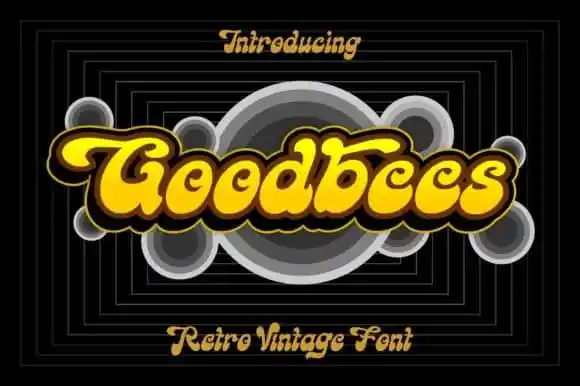
Goodbees Display Font – Download Grátis
A Goodbees Display Font é uma escolha perfeita para quem busca dar um toque vintage a seus projetos digitais. Inspirada no estilo retro dos anos 70, essa fonte se adequa perfeitamente a logotipos, citações escritas à mão, embalagens de produtos, cabeçalhos, flyers, merchandising, mídias sociais e até mesmo cartões de felicitações. Feita pelo designer ZetDesign, esta é uma fonte display chamativa, recheada de um charme retro que vai reviver aqueles tempos dos anos 70 em qualquer projeto. Seja para criar a identidade visual de seu novo produto ou dar um toque especial aos seus designs digitais, Goodbees Display Font certamente será sua fonte ideal. É uma maneira perfeita de transformar ideias em realidade com um estilo único e cativante.